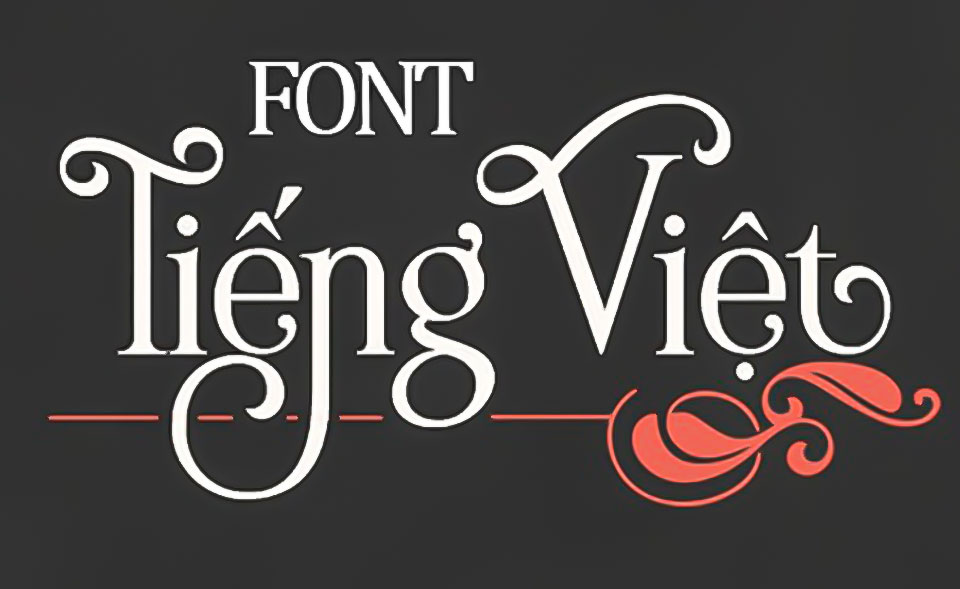
Cách Chọn Font Chữ Tiếng Việt Đẹp, Dễ Đọc Cho Mọi Dự Án [2025]
Chọn font chữ tiếng Việt phù hợp không chỉ là vấn đề thẩm mỹ, mà còn ảnh hưởng trực tiếp đến trải nghiệm đọc và hiệu quả truyền tải thông điệp trong mọi dự án thiết kế, từ website đến ấn phẩm in ấn. Bài viết này, thuộc chuyên mục Blog, sẽ đi sâu vào cách lựa chọn font chữ tối ưu, dễ đọc và phù hợp với từng mục đích sử dụng. Bạn sẽ được hướng dẫn chi tiết về các yếu tố quan trọng như kiểu chữ, độ tương phản, khoảng cách, khả năng hiển thị trên các thiết bị khác nhau, và cách kết hợp font chữ một cách hài hòa. Bên cạnh đó, chúng tôi cũng sẽ giới thiệu một số font chữ tiếng Việt đẹp và phổ biến, kèm theo các công cụ hữu ích giúp bạn dễ dàng tìm kiếm và quản lý font chữ cho dự án của mình, đảm bảo sự chuyên nghiệp và thu hút cho mọi sản phẩm.
Cách Chọn Font Chữ Tiếng Việt Đẹp, Dễ Đọc Cho Mọi Dự Án [2025]
Tại Sao Lựa Chọn Font Chữ Tiếng Việt Lại Quan Trọng Cho Mọi Dự Án?
Việc lựa chọn font chữ Tiếng Việt phù hợp đóng vai trò then chốt trong việc truyền tải thông điệp hiệu quả và xây dựng bản sắc thương hiệu cho mọi dự án thiết kế, marketing hay truyền thông. Quyết định này không chỉ ảnh hưởng đến tính thẩm mỹ của sản phẩm mà còn tác động trực tiếp đến trải nghiệm người dùng và khả năng tiếp cận thông tin. Một font chữ Tiếng Việt được lựa chọn cẩn thận sẽ góp phần tạo nên sự chuyên nghiệp, tăng cường khả năng đọc hiểu và thể hiện được cá tính riêng của dự án.
Font chữ không đơn thuần là công cụ hiển thị văn bản, mà còn là yếu tố quan trọng trong việc định hình nhận diện thương hiệu và truyền tải cảm xúc.
• Thể hiện sự chuyên nghiệp và uy tín: Một font chữ được thiết kế tỉ mỉ, dễ đọc và phù hợp với ngữ cảnh sẽ giúp dự án của bạn trở nên chuyên nghiệp và đáng tin cậy hơn. Ngược lại, việc sử dụng font chữ cẩu thả, khó đọc hoặc không phù hợp có thể gây ấn tượng tiêu cực và làm giảm giá trị của dự án. Ví dụ, một trang web sử dụng font chữ khó đọc sẽ khiến người dùng cảm thấy khó chịu và nhanh chóng rời đi, ảnh hưởng đến tỷ lệ chuyển đổi.
• Tăng cường khả năng đọc hiểu: Khả năng đọc hiểu là yếu tố then chốt để truyền tải thông điệp một cách hiệu quả. Một font chữ được thiết kế tốt sẽ có khoảng cách giữa các chữ, độ cao và độ dày phù hợp, giúp người đọc dễ dàng nhận biết và phân biệt các ký tự, từ đó cải thiện tốc độ đọc và khả năng ghi nhớ thông tin. Theo nghiên cứu của Baymard Institute, khả năng đọc hiểu là một trong những yếu tố quan trọng nhất ảnh hưởng đến trải nghiệm người dùng trên các trang web thương mại điện tử.
• Thể hiện cá tính và bản sắc thương hiệu: Mỗi font chữ mang một phong cách và cảm xúc riêng. Việc lựa chọn font chữ phù hợp sẽ giúp bạn thể hiện được cá tính và bản sắc riêng của thương hiệu, tạo sự khác biệt so với đối thủ cạnh tranh. Ví dụ, một thương hiệu thời trang cao cấp có thể sử dụng font chữ thanh lịch, sang trọng để thể hiện sự đẳng cấp, trong khi một thương hiệu đồ chơi trẻ em có thể sử dụng font chữ vui nhộn, ngộ nghĩnh để thu hút sự chú ý của trẻ em.
Cách Chọn Font Chữ Tiếng Việt Đẹp, Dễ Đọc Cho Mọi Dự Án [2025]
Việc xem xét kỹ lưỡng và lựa chọn font chữ Tiếng Việt phù hợp là một bước quan trọng để đảm bảo sự thành công của mọi dự án. Nó không chỉ ảnh hưởng đến tính thẩm mỹ và khả năng đọc hiểu, mà còn góp phần xây dựng thương hiệu và tạo ấn tượng tốt với người dùng.
Bí Quyết Chọn Font Chữ Tiếng Việt Đẹp, Dễ Đọc Theo Mục Đích Sử Dụng
Lựa chọn font chữ Tiếng Việt phù hợp là yếu tố then chốt để tạo nên một thiết kế thành công, truyền tải thông điệp hiệu quả. Tuy nhiên, để chọn font chữ Tiếng Việt đẹp, dễ đọc và phù hợp với từng mục đích sử dụng cụ thể, bạn cần nắm vững những bí quyết và nguyên tắc nhất định. Bài viết này sẽ cung cấp cho bạn những hướng dẫn chi tiết nhất, giúp bạn dễ dàng lựa chọn được font chữ ưng ý cho mọi dự án.
Việc lựa chọn kiểu chữ không chỉ đơn thuần là yếu tố thẩm mỹ mà còn ảnh hưởng trực tiếp đến khả năng tiếp nhận thông tin của người đọc. Một phông chữ được lựa chọn cẩn thận, đảm bảo tính dễ đọc sẽ giúp tăng cường trải nghiệm người dùng, đồng thời thể hiện sự chuyên nghiệp và tinh tế của người thiết kế. Dưới đây là những bí quyết vàng giúp bạn chọn được font chữ Tiếng Việt phù hợp, đáp ứng tối đa yêu cầu của từng dự án cụ thể.
Để chọn font chữ Tiếng Việt phù hợp, bạn cần xem xét các yếu tố sau:
• Mục đích sử dụng: Font chữ cho tiêu đề cần khác với font chữ cho nội dung văn bản. Tiêu đề cần gây ấn tượng, thu hút sự chú ý, trong khi nội dung văn bản cần đảm bảo tính dễ đọc, không gây mỏi mắt. Ví dụ, font chữ Playfair Display thường được sử dụng cho tiêu đề vì vẻ đẹp thanh lịch, trong khi Roboto lại được ưa chuộng cho nội dung vì tính rõ ràng, dễ đọc trên nhiều thiết bị.
• Đối tượng độc giả: Font chữ cho trẻ em cần khác với font chữ cho người lớn tuổi. Trẻ em thường thích những font chữ vui nhộn, ngộ nghĩnh, trong khi người lớn tuổi lại ưu tiên những font chữ đơn giản, rõ ràng, dễ nhìn. Ví dụ, Baloo Bhai 2 phù hợp với đối tượng trẻ em, còn Open Sans lại được ưa chuộng cho người lớn tuổi.
• Nền tảng hiển thị: Font chữ cho website cần khác với font chữ cho in ấn. Font chữ cho website cần được tối ưu hóa để hiển thị tốt trên các thiết bị khác nhau, trong khi font chữ cho in ấn cần đảm bảo độ sắc nét, không bị nhòe khi in. Theo Google Fonts, Lato là một lựa chọn phổ biến cho website vì khả năng hiển thị tốt trên nhiều trình duyệt, còn Times New Roman thường được dùng cho in ấn vì tính truyền thống, dễ đọc.
• Tính nhất quán: Sử dụng một vài font chữ nhất quán trong toàn bộ dự án để tạo sự chuyên nghiệp, tránh gây rối mắt cho người đọc. Nên chọn một font chữ chính cho tiêu đề và một font chữ phụ cho nội dung, đảm bảo chúng hài hòa về mặt thẩm mỹ. Ví dụ, bạn có thể kết hợp Montserrat cho tiêu đề và Raleway cho nội dung để tạo sự cân bằng, hiện đại.
Ngoài ra, hãy luôn kiểm tra kỹ lưỡng khả năng hiển thị của font chữ trên các thiết bị và trình duyệt khác nhau trước khi đưa vào sử dụng. Sử dụng các công cụ kiểm tra font chữ trực tuyến để đảm bảo tính dễ đọc và thẩm mỹ của font chữ bạn chọn.
Top Font Chữ Tiếng Việt Phổ Biến, Được Ưa Chuộng Nhất 2025
Việc lựa chọn font chữ tiếng Việt đẹp và dễ đọc là yếu tố then chốt trong mọi dự án thiết kế, và để giúp bạn cập nhật xu hướng mới nhất, chúng tôi xin giới thiệu top font chữ tiếng Việt hứa hẹn sẽ được ưa chuộng nhất trong năm 2025. Các font chữ này không chỉ đảm bảo tính thẩm mỹ cao mà còn đáp ứng các tiêu chuẩn về khả năng hiển thị tốt trên nhiều nền tảng và thiết bị khác nhau, từ đó góp phần nâng cao trải nghiệm người dùng.
Sự phổ biến của một font chữ không chỉ dựa vào vẻ ngoài mà còn phụ thuộc vào tính ứng dụng và khả năng truyền tải thông điệp hiệu quả. Các font chữ tiếng Việt được ưa chuộng trong năm 2025 dự kiến sẽ chú trọng vào sự cân bằng giữa nét truyền thống và hiện đại, mang đến sự linh hoạt cho nhiều loại hình thiết kế khác nhau, từ in ấn đến kỹ thuật số. Đồng thời, khả năng hiển thị tốt trên các thiết bị di động và độ phân giải cao cũng là một yếu tố quan trọng, đảm bảo trải nghiệm người dùng tối ưu trên mọi nền tảng.
Dưới đây là danh sách các font chữ tiếng Việt dự kiến sẽ thống trị thị trường thiết kế năm 2025:
• Lexend: Với thiết kế tối giản, dễ đọc, Lexend phù hợp cho cả tiêu đề và nội dung văn bản. Các biến thể của Lexend như Lexend Deca, Lexend Exa, Lexend Giga, Lexend Mega, Lexend Peta, Lexend Tera, và Lexend Zetta cung cấp nhiều lựa chọn về độ đậm và khoảng cách chữ, đáp ứng nhu cầu đa dạng của các dự án.
• Roboto: Một font sans-serif hiện đại, Roboto được biết đến với tính linh hoạt và dễ đọc trên nhiều kích cỡ màn hình khác nhau. Thiết kế rõ ràng và đơn giản của Roboto làm cho nó trở thành lựa chọn lý tưởng cho cả giao diện người dùng và nội dung văn bản dài.
• Open Sans: Là một font sans-serif khác được ưa chuộng, Open Sans có thiết kế thanh lịch và dễ đọc, phù hợp cho nhiều mục đích sử dụng khác nhau, từ trang web đến tài liệu in ấn. Sự rõ ràng và tính trung tính của Open Sans giúp nó dễ dàng kết hợp với các font chữ khác.
• Be Vietnam Pro: Được thiết kế dành riêng cho tiếng Việt, Be Vietnam Pro là một font sans-serif hiện đại với các ký tự được thiết kế tỉ mỉ, đảm bảo khả năng hiển thị tốt và tính thẩm mỹ cao. Font chữ này hỗ trợ đầy đủ các dấu tiếng Việt và có nhiều biến thể về độ đậm, giúp người dùng dễ dàng lựa chọn phiên bản phù hợp cho dự án của mình.
• Nunito Sans: Với các góc bo tròn mềm mại, Nunito Sans mang đến cảm giác thân thiện và dễ chịu cho người đọc. Font chữ này thích hợp cho các dự án thiết kế hướng đến đối tượng trẻ tuổi hoặc muốn truyền tải thông điệp gần gũi, ấm áp.
• Montserrat: Lấy cảm hứng từ thiết kế đô thị của Buenos Aires, Montserrat là một font sans-serif mạnh mẽ và hiện đại. Font chữ này thường được sử dụng cho các tiêu đề lớn hoặc các thiết kế mang tính tuyên bố.
• SVN-Gilroy: Là một font sans-serif hình học hiện đại. SVN-Gilroy mang đến vẻ ngoài sạch sẽ, chuyên nghiệp và có tính ứng dụng cao cho nhiều loại dự án thiết kế.
Việc lựa chọn font chữ phù hợp không chỉ là về mặt thẩm mỹ, mà còn ảnh hưởng đến trải nghiệm người dùng và hiệu quả truyền tải thông điệp. Bằng cách lựa chọn từ danh sách các font chữ tiếng Việt phổ biến và được ưa chuộng nhất 2025, bạn có thể đảm bảo rằng dự án của mình sẽ thu hút được sự chú ý và đạt được thành công mong đợi.
Hướng Dẫn Chi Tiết Cách Kiểm Tra Tính Dễ Đọc Của Font Chữ Tiếng Việt
Việc kiểm tra tính dễ đọc của font chữ Tiếng Việt là bước không thể bỏ qua trong quá trình chọn font chữ Tiếng Việt đẹp, dễ đọc cho bất kỳ dự án nào, bởi nó ảnh hưởng trực tiếp đến trải nghiệm và khả năng tiếp thu thông tin của người đọc. Một font chữ được đánh giá là dễ đọc khi nó giúp người đọc dễ dàng nhận diện từng con chữ, đọc liền mạch và không gây mỏi mắt khi đọc trong thời gian dài.
Để đánh giá một font chữ Tiếng Việt có thực sự dễ đọc hay không, bạn cần xem xét đến nhiều yếu tố khác nhau. Dưới đây là hướng dẫn chi tiết các bước và tiêu chí quan trọng cần lưu ý:
• Đánh giá khoảng cách giữa các chữ cái (letter-spacing): Khoảng cách giữa các chữ cái cần đủ rộng để người đọc dễ dàng phân biệt, tránh tình trạng các chữ cái dính liền vào nhau, gây khó khăn cho việc đọc. Ví dụ, một số font chữ có thiết kế quá sát nhau sẽ khiến người đọc dễ nhầm lẫn giữa các chữ “n” và “u”, hoặc “m” và “rn”.
• Kiểm tra chiều cao chữ thường (x-height): Chiều cao chữ thường, đặc biệt là chữ “x”, đóng vai trò quan trọng trong việc tạo nên sự hài hòa và dễ đọc của font chữ. Chiều cao chữ thường lý tưởng thường chiếm khoảng 50-70% chiều cao chữ hoa.
• Xem xét độ dày nét chữ (stroke thickness): Độ dày nét chữ cần cân đối, không quá đậm gây rối mắt, cũng không quá mảnh khiến chữ bị nhạt nhòa, khó nhìn. Một số font chữ có độ tương phản cao giữa nét đậm và nét thanh có thể gây mỏi mắt khi đọc lâu.
• Đánh giá hình dạng chữ cái (character shapes): Hình dạng các chữ cái cần rõ ràng, dễ phân biệt, đặc biệt là các chữ có hình dáng tương đồng như “o”, “a”, “d”, “q”, “p”, “b”.
• Kiểm tra dấu câu và ký tự đặc biệt: Dấu câu và ký tự đặc biệt cần được thiết kế rõ ràng, dễ nhận diện, tránh tình trạng bị lẫn vào chữ cái hoặc bị mờ nhạt.
• Thử nghiệm với các kích cỡ chữ khác nhau (font size): Một font chữ có thể dễ đọc ở kích thước lớn nhưng lại khó đọc ở kích thước nhỏ và ngược lại. Hãy thử nghiệm với các kích cỡ chữ khác nhau để đảm bảo font chữ vẫn dễ đọc trong mọi trường hợp.
• Đọc thử văn bản dài: Cách tốt nhất để đánh giá tính dễ đọc của font chữ là đọc thử một đoạn văn bản dài. Hãy chú ý xem bạn có cảm thấy mỏi mắt hay khó chịu khi đọc hay không.
• Kiểm tra trên các thiết bị khác nhau: Giao diện hiển thị font chữ có thể khác nhau trên các thiết bị khác nhau (máy tính, điện thoại, máy tính bảng). Hãy kiểm tra font chữ trên nhiều thiết bị để đảm bảo tính dễ đọc.
Bằng việc áp dụng các bước kiểm tra trên, bạn có thể đánh giá một cách khách quan tính dễ đọc của font chữ Tiếng Việt và lựa chọn được font chữ phù hợp nhất cho dự án của mình, góp phần nâng cao trải nghiệm người dùng và truyền tải thông tin một cách hiệu quả nhất.
Kết Hợp Font Chữ Tiếng Việt: Nguyên Tắc Vàng Tạo Nên Thiết Kế Ấn Tượng
Việc kết hợp font chữ Tiếng Việt một cách hài hòa đóng vai trò then chốt trong việc tạo ra những thiết kế ấn tượng và chuyên nghiệp, góp phần nâng cao trải nghiệm người dùng và truyền tải thông điệp một cách hiệu quả nhất, đặc biệt quan trọng khi bạn tìm cách chọn font chữ Tiếng Việt đẹp, dễ đọc cho mọi dự án. Lựa chọn đúng font chữ Tiếng Việt và biết cách phối hợp chúng sẽ giúp thiết kế của bạn trở nên thu hút, dễ đọc và truyền tải đúng tinh thần của thương hiệu. Sự kết hợp khéo léo giữa các kiểu chữ khác nhau tạo nên sự tương phản, làm nổi bật các yếu tố quan trọng và mang đến sự độc đáo, cá tính cho tổng thể thiết kế.
Để tạo ra sự cân bằng thị giác, nguyên tắc đầu tiên và quan trọng nhất là tính tương phản. Hãy lựa chọn các font chữ có sự khác biệt rõ rệt về kiểu dáng, kích thước, độ dày và khoảng cách giữa các chữ. Ví dụ, bạn có thể kết hợp một font sans-serif hiện đại, tối giản cho tiêu đề với một font serif cổ điển, trang trọng cho nội dung chính. Sự tương phản này không chỉ giúp phân cấp thông tin rõ ràng mà còn tạo điểm nhấn và thu hút sự chú ý của người đọc vào những chi tiết quan trọng. Quan trọng nhất, hãy đảm bảo rằng sự kết hợp này không gây rối mắt hoặc khó đọc.
Sự hài hòa trong kết hợp font chữ còn nằm ở việc lựa chọn các font có chung ngữ cảnh hoặc phong cách. Nếu bạn đang thiết kế một ấn phẩm mang phong cách cổ điển, hãy tìm kiếm các font serif có đường nét mềm mại, tinh tế và kết hợp chúng một cách khéo léo. Ngược lại, với một thiết kế hiện đại, năng động, các font sans-serif mạnh mẽ, cá tính sẽ là lựa chọn phù hợp. Việc hiểu rõ ngữ cảnh và mục đích của thiết kế sẽ giúp bạn lựa chọn được những font chữ có sự tương đồng về tinh thần và cảm xúc, từ đó tạo nên một tổng thể thống nhất và hài hòa.
Bên cạnh đó, hãy chú ý đến số lượng font chữ sử dụng trong một thiết kế. Nguyên tắc chung là không nên sử dụng quá 3 font khác nhau trong cùng một dự án. Việc sử dụng quá nhiều font sẽ khiến thiết kế trở nên rối mắt, thiếu chuyên nghiệp và gây khó khăn cho người đọc trong việc tiếp nhận thông tin. Thay vào đó, hãy tập trung vào việc khai thác tối đa các biến thể của một font chữ (ví dụ: in đậm, in nghiêng, kích thước khác nhau) để tạo sự đa dạng và phong phú cho thiết kế mà vẫn đảm bảo được tính thống nhất và hài hòa.
Cuối cùng, một yếu tố quan trọng không thể bỏ qua là khả năng đọc của font chữ. Dù bạn có kết hợp các font một cách sáng tạo đến đâu, điều quan trọng nhất vẫn là đảm bảo rằng người đọc có thể dễ dàng tiếp nhận thông tin mà bạn muốn truyền tải. Hãy kiểm tra kỹ lưỡng khoảng cách giữa các chữ, độ tương phản giữa chữ và nền, và kích thước chữ để đảm bảo rằng font chữ của bạn dễ đọc trên mọi thiết bị và trong mọi điều kiện ánh sáng.
Công Cụ Hỗ Trợ Tìm Kiếm và Quản Lý Font Chữ Tiếng Việt Hiệu Quả
Để cách chọn font chữ tiếng Việt đẹp, dễ đọc cho mọi dự án trở nên dễ dàng hơn, việc sử dụng các công cụ hỗ trợ tìm kiếm và quản lý font chữ là vô cùng quan trọng. Các công cụ này không chỉ giúp bạn khám phá vô vàn lựa chọn font chữ, mà còn đơn giản hóa quá trình quản lý, tổ chức và thử nghiệm các font chữ khác nhau.
Việc lựa chọn typeface phù hợp là một yếu tố then chốt để tạo nên một thiết kế ấn tượng và chuyên nghiệp. Các công cụ quản lý font chữ hiệu quả sẽ giúp bạn tiết kiệm thời gian, tối ưu quy trình làm việc và nâng cao chất lượng sản phẩm cuối cùng. Dưới đây là một số công cụ hỗ trợ tìm kiếm và quản lý font chữ Tiếng Việt mà bạn có thể tham khảo:
• Google Fonts: Đây là một thư viện font chữ miễn phí khổng lồ, cung cấp nhiều lựa chọn font chữ Tiếng Việt chất lượng cao. Bạn có thể dễ dàng tìm kiếm, lọc và tải xuống các font chữ phù hợp với nhu cầu của mình. Ưu điểm nổi bật của Google Fonts là tính tương thích cao với các trình duyệt web và các ứng dụng thiết kế phổ biến.
• Font Squirrel: Tương tự như Google Fonts, Font Squirrel cũng là một nguồn tài nguyên font chữ miễn phí tuyệt vời. Điểm khác biệt là Font Squirrel tập trung vào các font chữ có giấy phép thương mại, cho phép bạn sử dụng chúng trong các dự án cá nhân và thương mại mà không lo ngại về vấn đề bản quyền.
• Adobe Fonts (Typekit): Nếu bạn là người dùng Adobe Creative Cloud, bạn sẽ có quyền truy cập vào Adobe Fonts, một thư viện font chữ phong phú với hàng ngàn lựa chọn typeface chất lượng cao. Adobe Fonts tích hợp trực tiếp với các ứng dụng Adobe như Photoshop, Illustrator và InDesign, giúp bạn dễ dàng tìm kiếm, kích hoạt và sử dụng các font chữ trong các dự án thiết kế của mình.
• FontBase: Đây là một trình quản lý font chữ mạnh mẽ, cho phép bạn tổ chức, xem trước và kích hoạt các font chữ một cách dễ dàng. FontBase hỗ trợ nhiều định dạng font chữ khác nhau, bao gồm OpenType, TrueType và PostScript. Ngoài ra, FontBase còn có tính năng tự động kích hoạt font chữ khi bạn mở một tài liệu cần font chữ đó, giúp bạn tiết kiệm thời gian và công sức.
• NexusFont: Tương tự như FontBase, NexusFont là một trình quản lý font chữ miễn phí, cung cấp các tính năng cơ bản để bạn tổ chức và quản lý font chữ. NexusFont cho phép bạn tạo các bộ sưu tập font chữ, xem trước font chữ với các đoạn văn bản tùy chỉnh và tìm kiếm font chữ theo tên, kiểu dáng hoặc các thuộc tính khác.
• RightFont: RightFont là một trình quản lý font chữ trả phí, cung cấp nhiều tính năng nâng cao để giúp bạn quản lý font chữ một cách chuyên nghiệp. RightFont tích hợp với các ứng dụng thiết kế phổ biến như Photoshop, Illustrator và Sketch, cho phép bạn xem trước font chữ trực tiếp trong các ứng dụng này. Ngoài ra, RightFont còn có tính năng tự động đồng bộ font chữ giữa các thiết bị, giúp bạn dễ dàng truy cập vào font chữ của mình từ bất kỳ đâu.
Sử dụng các công cụ hỗ trợ tìm kiếm và quản lý font chữ không chỉ giúp bạn tìm thấy typeface ưng ý, mà còn giúp bạn quản lý bộ sưu tập font chữ của mình một cách hiệu quả. Điều này giúp bạn tiết kiệm thời gian, nâng cao hiệu suất làm việc và tạo ra những thiết kế ấn tượng hơn.
Lưu Ý Quan Trọng Khi Sử Dụng Font Chữ Tiếng Việt Để Tránh Sai Sót
Việc sử dụng font chữ Tiếng Việt một cách cẩn trọng là yếu tố then chốt để đảm bảo tính chuyên nghiệp và hiệu quả của mọi dự án thiết kế, đặc biệt khi cách chọn font chữ Tiếng Việt đẹp, dễ đọc đang ngày càng được quan tâm. Lựa chọn sai font chữ có thể dẫn đến những sai sót không đáng có, ảnh hưởng trực tiếp đến trải nghiệm người dùng và uy tín của thương hiệu. Để tránh những lỗi phổ biến và tối ưu hóa hiệu quả truyền tải thông điệp, người thiết kế cần nắm vững những nguyên tắc và lưu ý quan trọng khi làm việc với font chữ Tiếng Việt.
Một trong những sai sót thường gặp là lỗi hiển thị Tiếng Việt, xuất phát từ việc font chữ không hỗ trợ đầy đủ các ký tự đặc biệt của bảng chữ cái Tiếng Việt (ví dụ: dấu sắc, huyền, hỏi, ngã, nặng). Điều này dẫn đến việc các ký tự bị hiển thị sai lệch, gây khó khăn cho việc đọc hiểu và làm mất đi tính thẩm mỹ của văn bản. Trước khi sử dụng bất kỳ font chữ nào, cần kiểm tra kỹ lưỡng bảng mã ký tự để đảm bảo rằng nó hỗ trợ đầy đủ Tiếng Việt, đặc biệt là các dấu thanh.
Để đảm bảo tính dễ đọc, cần chú ý đến các yếu tố sau:
• Khoảng cách giữa các chữ cái và dòng: Khoảng cách quá hẹp hoặc quá rộng đều gây khó khăn cho việc nhận diện chữ.
• Độ tương phản: Màu chữ và màu nền cần có độ tương phản đủ lớn để người đọc dễ dàng phân biệt.
• Kích thước chữ: Kích thước chữ quá nhỏ sẽ khiến người đọc phải căng mắt, trong khi kích thước quá lớn lại gây cảm giác thô kệch.
• Độ dày của nét chữ: Nét chữ quá mỏng có thể bị nhòe, còn nét chữ quá đậm lại gây cảm giác nặng nề.
Việc lạm dụng quá nhiều font chữ trong một dự án cũng là một sai lầm cần tránh. Sử dụng quá nhiều font chữ khác nhau có thể khiến thiết kế trở nên rối mắt, thiếu chuyên nghiệp và gây mất tập trung cho người đọc. Nên giới hạn số lượng font chữ sử dụng trong một dự án ở mức 2-3 font và lựa chọn các font chữ có sự tương đồng về phong cách để tạo sự hài hòa cho thiết kế.
Ngoài ra, cần lưu ý đến vấn đề bản quyền khi sử dụng font chữ. Nhiều font chữ được cung cấp miễn phí nhưng lại có các điều khoản sử dụng khác nhau. Việc sử dụng font chữ vi phạm bản quyền có thể dẫn đến các rắc rối pháp lý. Hãy tìm hiểu kỹ về giấy phép sử dụng trước khi sử dụng bất kỳ font chữ nào cho dự án của bạn.
Cuối cùng, hãy luôn kiểm tra kỹ lưỡng văn bản sau khi đã chọn font chữ. Đảm bảo rằng tất cả các ký tự Tiếng Việt đều được hiển thị đúng cách, không có lỗi chính tả, và bố cục văn bản hài hòa, dễ đọc. Việc kiểm tra kỹ lưỡng sẽ giúp bạn phát hiện và khắc phục các sai sót trước khi dự án được hoàn thành, đảm bảo chất lượng và tính chuyên nghiệp của sản phẩm cuối cùng.
Cập Nhật Về Luật Bản Quyền Font Chữ Tiếng Việt Năm 2025 và Cách Tuân Thủ
Việc am hiểu và tuân thủ luật bản quyền font chữ Tiếng Việt là yếu tố then chốt để đảm bảo tính hợp pháp và tránh các rủi ro pháp lý trong mọi dự án thiết kế, in ấn, hay xuất bản. Cập nhật về những thay đổi trong luật bản quyền font chữ Tiếng Việt năm 2025 và các biện pháp tuân thủ sẽ giúp bạn sử dụng font chữ một cách an toàn và hiệu quả, đồng thời bảo vệ quyền lợi của nhà thiết kế font.
Những điểm mới trong Luật Bản Quyền Font Chữ Tiếng Việt năm 2025
Năm 2025, luật bản quyền font chữ Tiếng Việt chứng kiến những thay đổi quan trọng, ảnh hưởng trực tiếp đến cách các nhà thiết kế, doanh nghiệp và người dùng sử dụng font chữ. Cụ thể:
• Mở rộng phạm vi bảo vệ: Luật mới có thể mở rộng phạm vi bảo vệ bản quyền không chỉ cho các thiết kế font chữ gốc, mà còn cho các biến thể, điều chỉnh nhỏ dựa trên font gốc. Điều này nhằm khuyến khích sự sáng tạo và bảo vệ quyền lợi của tác giả một cách toàn diện hơn.
• Quy định rõ ràng về sử dụng thương mại: Luật làm rõ hơn các quy định về việc sử dụng font chữ cho mục đích thương mại, bao gồm cả việc sử dụng font trong logo, quảng cáo, bao bì sản phẩm, và các ấn phẩm marketing khác. Các điều khoản cấp phép có thể chặt chẽ hơn, yêu cầu người dùng phải có giấy phép phù hợp để sử dụng font cho các mục đích này.
• Tăng cường chế tài xử phạt: Mức phạt cho hành vi vi phạm bản quyền font chữ có thể tăng lên đáng kể, bao gồm cả phạt tiền và các biện pháp pháp lý khác. Điều này nhằm răn đe các hành vi xâm phạm bản quyền và bảo vệ quyền lợi của chủ sở hữu font chữ.
Làm thế nào để tuân thủ Luật Bản Quyền Font Chữ Tiếng Việt năm 2025?
Để đảm bảo tuân thủ luật bản quyền font chữ Tiếng Việt năm 2025, bạn cần thực hiện các bước sau:
• Kiểm tra giấy phép sử dụng: Luôn kiểm tra kỹ giấy phép sử dụng font chữ trước khi sử dụng cho bất kỳ mục đích nào, đặc biệt là mục đích thương mại. Đảm bảo rằng giấy phép cho phép bạn sử dụng font cho loại hình dự án mà bạn đang thực hiện.
• Sử dụng font chữ có bản quyền: Chỉ sử dụng font chữ được cung cấp bởi các nhà cung cấp uy tín hoặc từ các nguồn font có bản quyền rõ ràng. Tránh sử dụng font chữ miễn phí không rõ nguồn gốc, vì chúng có thể vi phạm bản quyền.
• Lưu trữ giấy phép cẩn thận: Lưu trữ cẩn thận các giấy phép sử dụng font chữ để có thể chứng minh quyền sử dụng hợp pháp khi cần thiết.
• Cập nhật kiến thức pháp luật: Thường xuyên cập nhật kiến thức về luật bản quyền font chữ để nắm bắt những thay đổi mới nhất và đảm bảo tuân thủ đầy đủ.
Các nguồn tài nguyên để tìm hiểu về Luật Bản Quyền Font Chữ
Để hiểu rõ hơn về luật bản quyền font chữ Tiếng Việt và cách tuân thủ, bạn có thể tham khảo các nguồn tài nguyên sau:
• Văn bản pháp luật: Tìm đọc các văn bản pháp luật liên quan đến bản quyền tác giả, bao gồm cả các quy định về font chữ.
• Website của các tổ chức bản quyền: Truy cập website của các tổ chức bảo vệ bản quyền để tìm hiểu thông tin về bản quyền font chữ.
• Tư vấn luật sư: Tham khảo ý kiến của luật sư chuyên về bản quyền để được tư vấn cụ thể về trường hợp của bạn.
Việc tuân thủ luật bản quyền font chữ không chỉ là trách nhiệm pháp lý mà còn là hành động thể hiện sự tôn trọng đối với quyền sở hữu trí tuệ của các nhà thiết kế font. Bằng cách sử dụng font chữ một cách hợp pháp, bạn góp phần xây dựng một môi trường sáng tạo bền vững và khuyến khích sự phát triển của ngành thiết kế font chữ Việt Nam.
Case Study: Phân Tích Lựa Chọn Font Chữ Thành Công Trong Các Dự Án Thực Tế
Việc lựa chọn font chữ phù hợp không chỉ là vấn đề thẩm mỹ, mà còn đóng vai trò then chốt trong việc truyền tải thông điệp và tạo dựng thương hiệu mạnh mẽ. Trong phần này, chúng ta sẽ đi sâu vào các case study thực tế để phân tích cách các doanh nghiệp đã thành công trong việc chọn font chữ tiếng Việt cho các dự án của mình, từ đó rút ra những bài học giá trị về cách chọn font chữ tiếng Việt đẹp, dễ đọc cho mọi dự án. Các ví dụ này không chỉ giúp ta hiểu rõ hơn về tầm quan trọng của font chữ mà còn cung cấp cái nhìn sâu sắc về quá trình lựa chọn và ứng dụng font chữ trong thực tế.
Một ví dụ điển hình là chiến dịch tái thiết kế thương hiệu của Vinamilk năm 2023. Thay vì sử dụng font chữ cũ có phần cứng nhắc, Vinamilk đã lựa chọn font Rubik, một font sans-serif hiện đại, thân thiện và dễ đọc. Quyết định này đã giúp Vinamilk truyền tải thông điệp về sự đổi mới, năng động và gần gũi hơn với người tiêu dùng. Phân tích kỹ hơn, ta thấy font Rubik có độ dày vừa phải, khoảng cách giữa các chữ rộng rãi, và các đường nét bo tròn tạo cảm giác mềm mại, dễ chịu cho mắt. Điều này đặc biệt quan trọng đối với một thương hiệu sữa hướng đến đối tượng gia đình và trẻ em. Ngoài ra, việc sử dụng màu sắc tươi sáng và cách bố trí hài hòa cũng góp phần làm nổi bật font chữ và tăng cường hiệu quả truyền thông.
Xét một trường hợp khác, trang web của Tiki, một trong những sàn thương mại điện tử hàng đầu Việt Nam, sử dụng chủ yếu font Open Sans. Open Sans là một font sans-serif phổ biến với thiết kế rõ ràng, đơn giản và dễ đọc trên nhiều thiết bị. Việc Tiki ưu tiên Open Sans thể hiện sự chú trọng đến trải nghiệm người dùng, đặc biệt là trên các thiết bị di động. Bởi lẽ, khi chọn font chữ tiếng Việt, yếu tố dễ đọc trên màn hình là vô cùng quan trọng, nhất là với một trang web có lượng truy cập lớn và nội dung đa dạng như Tiki. Thống kê cho thấy, tỷ lệ thoát trang của Tiki đã giảm đáng kể sau khi họ tối ưu hóa font chữ và bố cục trang web, chứng minh rằng việc lựa chọn font chữ phù hợp có thể tác động trực tiếp đến hiệu quả kinh doanh.
Cuối cùng, hãy xem xét cách mà các tạp chí thời trang hàng đầu tại Việt Nam như ELLE, Harper’s Bazaar sử dụng font chữ trong thiết kế của họ. Các tạp chí này thường kết hợp một font serif thanh lịch cho tiêu đề (ví dụ: Playfair Display hoặc Lora) và một font sans-serif đơn giản cho nội dung (ví dụ: Roboto hoặc Nunito Sans). Sự kết hợp này tạo ra sự tương phản thú vị, giúp thu hút sự chú ý của độc giả và làm nổi bật nội dung quan trọng. Bên cạnh đó, việc lựa chọn font chữ tiếng Việt có chân thanh lịch cho tiêu đề còn thể hiện sự sang trọng, tinh tế và đẳng cấp, phù hợp với hình ảnh mà các tạp chí thời trang muốn xây dựng. Có thể thấy sự kết hợp hài hòa của font chữ và bố cục là chìa khóa để tạo ra một ấn phẩm thời trang đẹp mắt và chuyên nghiệp.
Tương Lai Của Font Chữ Tiếng Việt: Xu Hướng Thiết Kế Mới Nhất và Dự Đoán
Font chữ Tiếng Việt không chỉ là công cụ truyền tải thông tin mà còn là yếu tố quan trọng tạo nên bản sắc văn hóa và dấu ấn thương hiệu, do đó việc nắm bắt xu hướng thiết kế font chữ và dự đoán tương lai của chúng là vô cùng cần thiết để tạo ra những sản phẩm thiết kế ấn tượng và hiệu quả. Trong bối cảnh công nghệ phát triển vượt bậc và nhu cầu thẩm mỹ ngày càng cao, tương lai của font chữ Tiếng Việt hứa hẹn sẽ chứng kiến nhiều đổi mới và sáng tạo đột phá. Các xu hướng thiết kế mới nhất không chỉ tập trung vào tính thẩm mỹ mà còn chú trọng đến khả năng ứng dụng linh hoạt và tính dễ đọc trên mọi nền tảng.
Sự phát triển của công nghệ và sự thay đổi trong thị hiếu người dùng đang định hình tương lai của font chữ Tiếng Việt theo những hướng đi đầy tiềm năng.
• Font chữ biến thể (Variable Fonts): Xu hướng font chữ biến thể cho phép tùy chỉnh các thuộc tính như độ đậm, chiều rộng, độ nghiêng một cách linh hoạt, giúp tối ưu hóa trải nghiệm đọc trên nhiều thiết bị và kích thước màn hình. Điều này không chỉ tăng tính tương tác mà còn giảm dung lượng tệp tin, cải thiện hiệu suất website và ứng dụng. Chẳng hạn, một website có thể sử dụng cùng một font chữ cho cả tiêu đề và nội dung, nhưng điều chỉnh độ đậm và kích thước khác nhau để tạo sự phân cấp rõ ràng.
• Font chữ mang đậm dấu ấn cá nhân và văn hóa: Các nhà thiết kế ngày càng chú trọng đến việc tạo ra những font chữ độc đáo, mang đậm bản sắc văn hóa Việt Nam. Điều này có thể thể hiện qua việc sử dụng các yếu tố truyền thống như hình ảnh hoa sen, chim lạc, hoặc các họa tiết dân gian trong thiết kế chữ. Ví dụ, một thương hiệu thời trang có thể sử dụng một font chữ được thiết kế dựa trên kiểu chữ thư pháp cổ để tạo sự khác biệt và thể hiện giá trị văn hóa.
• Font chữ tối ưu cho giao diện người dùng (UI) và trải nghiệm người dùng (UX): Với sự phát triển của các ứng dụng di động và website, nhu cầu về font chữ dễ đọc, dễ nhìn trên các thiết bị điện tử ngày càng tăng cao. Các font chữ trong tương lai sẽ được thiết kế đặc biệt để tối ưu hóa trải nghiệm người dùng, đảm bảo khả năng đọc tốt trong mọi điều kiện ánh sáng và kích thước màn hình. Điều này đòi hỏi các nhà thiết kế phải nghiên cứu kỹ lưỡng về khoảng cách giữa các chữ cái, độ dày của nét chữ, và các yếu tố khác ảnh hưởng đến khả năng đọc.
• Ứng dụng Trí tuệ Nhân tạo (AI) trong thiết kế font chữ: AI đang dần trở thành một công cụ hỗ trợ đắc lực cho các nhà thiết kế font chữ, giúp tự động hóa các quy trình phức tạp và tạo ra những thiết kế độc đáo. AI có thể được sử dụng để tạo ra các biến thể font chữ dựa trên một kiểu chữ gốc, hoặc để tối ưu hóa font chữ cho các mục đích sử dụng khác nhau. Ví dụ, AI có thể giúp tạo ra một font chữ đặc biệt dành cho người khiếm thị, với các đặc điểm được tối ưu hóa để dễ đọc hơn.
Những xu hướng này cho thấy tương lai của font chữ Tiếng Việt sẽ ngày càng đa dạng, linh hoạt và cá nhân hóa. Việc lựa chọn font chữ phù hợp sẽ trở thành một yếu tố quan trọng hơn bao giờ hết trong việc tạo ra những sản phẩm thiết kế ấn tượng và hiệu quả, góp phần nâng cao trải nghiệm người dùng và thể hiện bản sắc văn hóa Việt Nam trên thị trường quốc tế.